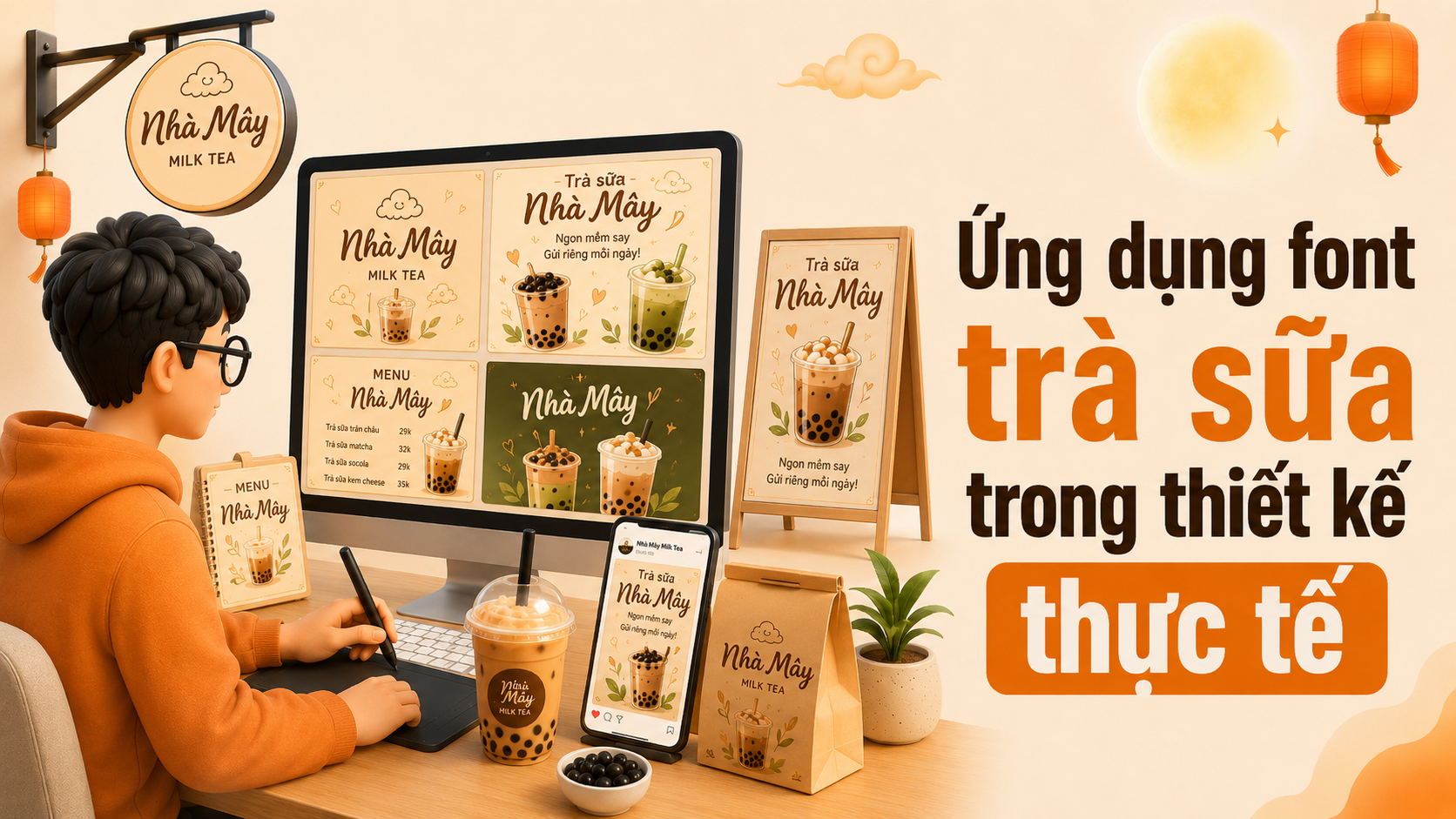
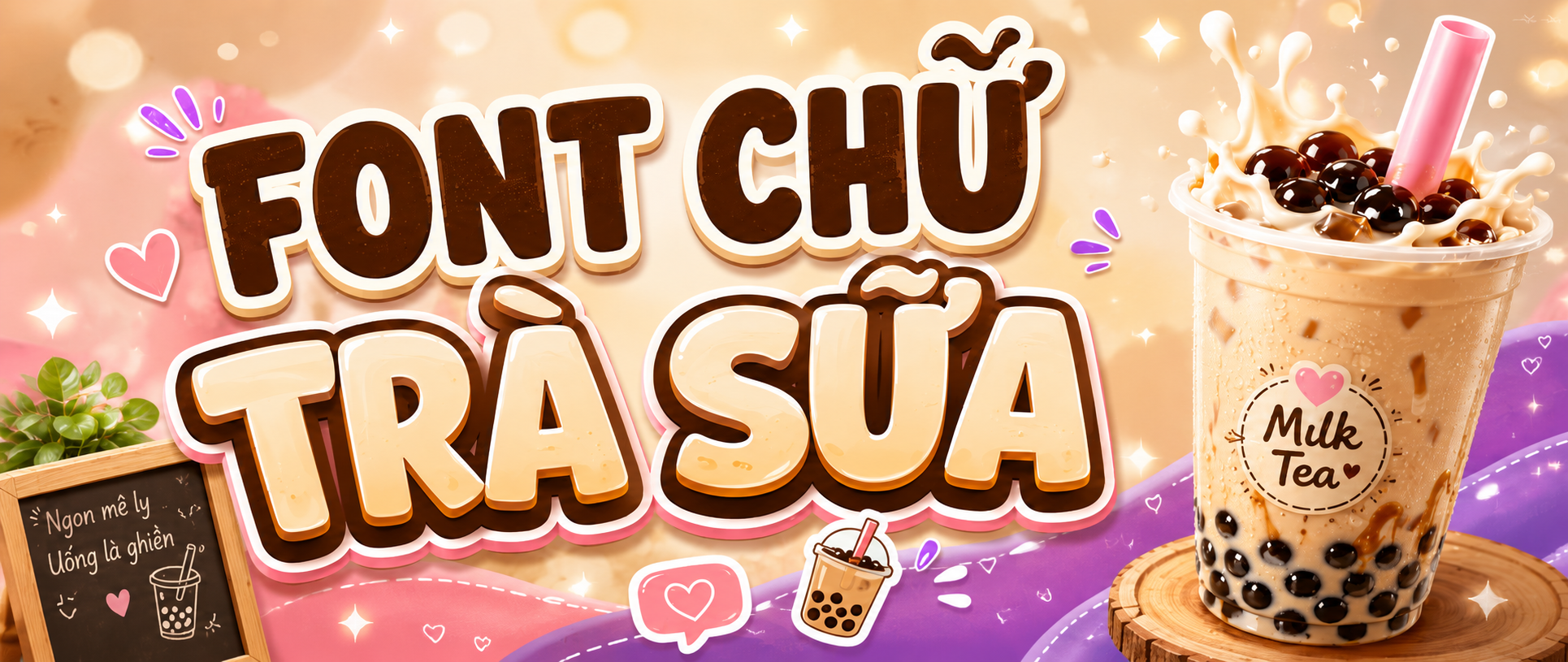
Thiết kế trà sữa cần cảm giác trẻ, ngon, vui và dễ gọi món. Một menu có nhiều topping, size, combo, món mới và giá khuyến mãi sẽ rất dễ rối nếu chọn sai font. Vì vậy, font chữ trà sữa nên vừa đáng yêu, vừa rõ tiếng Việt, vừa đủ nổi bật để dùng cho menu, ly nhãn, poster đồ uống và bảng giá sau quầy.
Bài viết này gợi ý các font TH/Việt hóa phù hợp cho quán trà sữa, đồ uống take away, kem, bánh ngọt và đồ ăn vặt. Mỗi font được đặt thành một dòng riêng kèm link tải trên S99 để bạn dễ chọn, tải và thử vào thiết kế thực tế.
Trà sữa là ngành hàng có rất nhiều thông tin nhỏ: tên món, vị trà, topping, đường đá, size, giá, combo và chương trình ưu đãi. Nếu font quá mảnh hoặc quá cách điệu, khách sẽ khó đọc menu. Nếu font quá cứng, thiết kế lại mất cảm giác ngọt, trẻ và vui.
Font trà sữa thường cần tạo cảm giác thân thiện hơn font nhà hàng. Các nét bo tròn, mũm mĩm, viết tay nhẹ hoặc display cute sẽ giúp menu nhìn gần gũi. Tuy nhiên, không phải phần nào cũng nên dùng font cute. Giá tiền, size và topping vẫn cần font rõ, dễ đọc và căn hàng gọn.
Một thiết kế trà sữa đẹp thường dùng 2-3 kiểu chữ. Font nổi bật dùng cho tên món signature, headline poster hoặc tiêu đề nhóm. Font dễ đọc dùng cho danh sách topping, mô tả, giá và ghi chú. Font phụ có thể dùng cho nhãn nhỏ như “new”, “best seller”, “less sugar” hoặc “combo”.
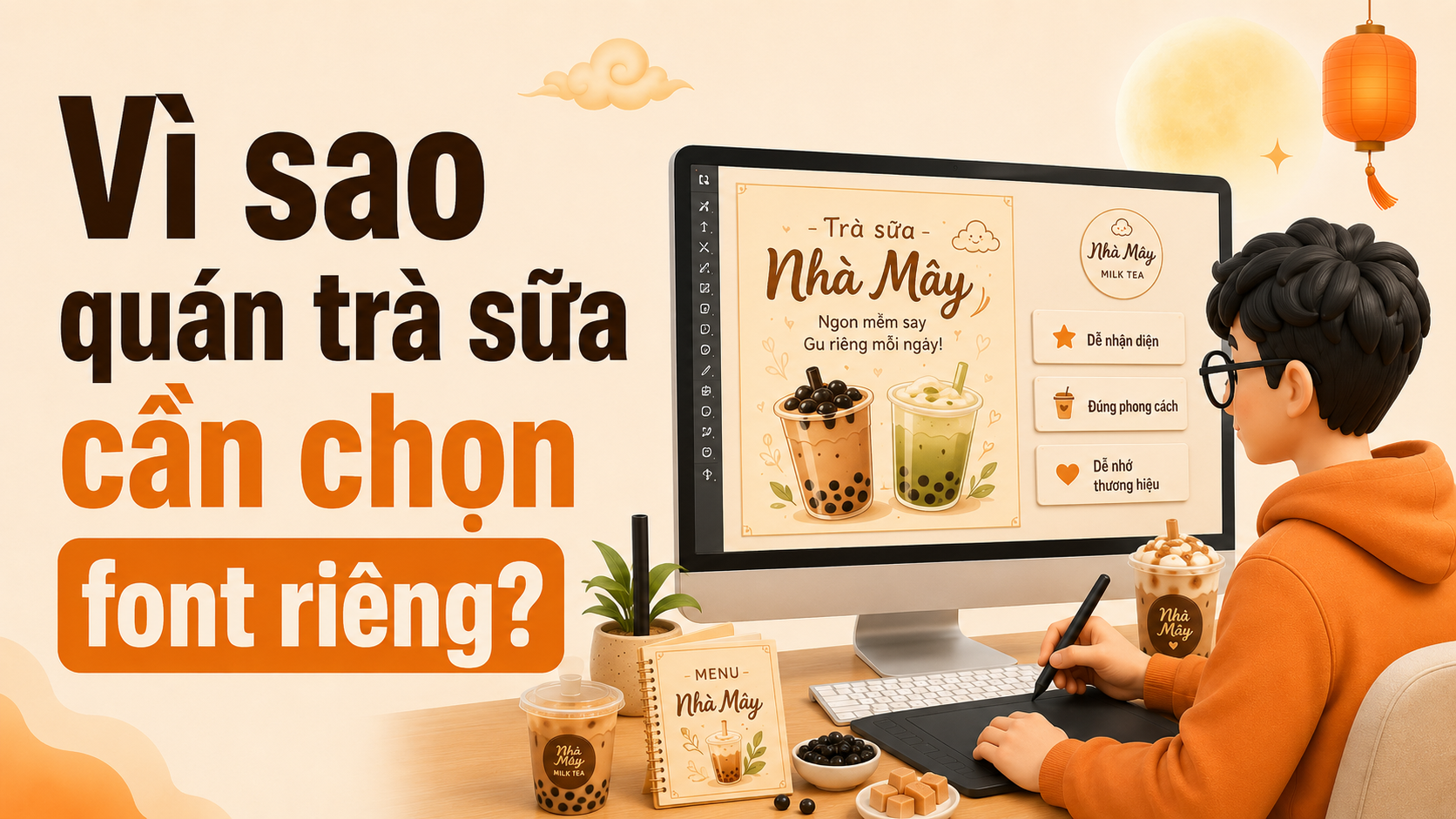
Menu trà sữa có nhiều chữ dễ lỗi dấu như sữa, đường, đá, trân châu, thạch, kem cheese, đậu đỏ, vải, đào, dâu. Font Việt hóa giúp dấu rõ và tránh tình trạng chữ bị lệch, mất dấu hoặc không đồng bộ.
Font mập, bo tròn và hoạt hình rất hợp trà sữa, nhưng nếu dùng cho toàn bộ menu sẽ gây rối. Hãy dùng font cute cho tiêu đề và món nổi bật, còn phần mô tả hoặc giá nên dùng font gọn hơn.
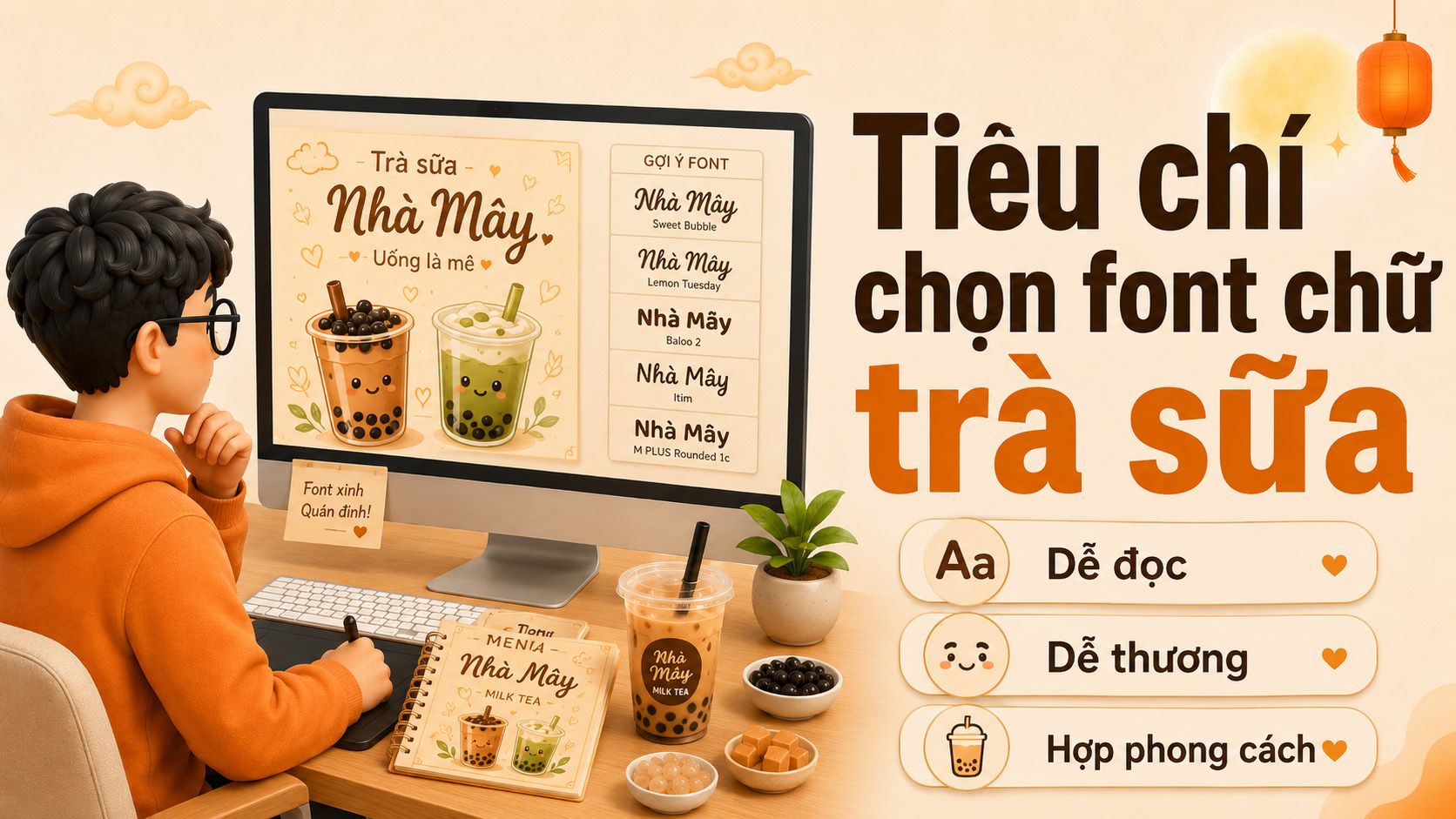
Quán trà sữa pastel hợp font mềm, tròn, nhẹ. Quán trà sữa đường phố hợp font đậm và năng động. Quán trà sữa cao cấp hoặc tea house nên dùng font thanh lịch hơn, tránh quá trẻ con.
Một font tốt nên dùng được cho menu giấy, menu treo tường, ly nhãn, poster Facebook, banner khai trương và story khuyến mãi. Nếu font chỉ đẹp ở cỡ lớn nhưng khó đọc ở cỡ nhỏ, chỉ nên dùng làm headline.
Ảnh ly trà sữa thường có nhiều chi tiết như đá, topping, foam, trái cây. Font cần có nét đủ mạnh để không chìm trên nền ảnh. Nếu nền phức tạp, nên đặt chữ trong khung màu hoặc vùng trắng.
Nhóm này hợp với poster món mới, banner khai trương, menu topping, sticker “best seller” và tên món cần nổi bật. Nét chữ tròn giúp thiết kế nhìn ngọt và vui hơn.
Những font này nên dùng ở kích thước lớn. Ví dụ: “Trà sữa trân châu”, “Matcha kem cheese”, “Combo 2 ly”, “Món mới”. Với bảng giá nhỏ, hãy chuyển sang font sans-serif để giữ độ rõ.
Nếu quán bán thêm bánh, kem, khoai, gà rán, xúc xích hoặc đồ ăn vặt, nhóm font hoạt hình giúp poster nhìn sinh động hơn. Font có cá tính mạnh nên dùng cho điểm nhấn thay vì toàn bộ menu.
Với poster topping, hãy phối font hoạt hình cùng màu sáng như hồng, kem, nâu sữa, xanh mint hoặc vàng bơ. Không nên dùng quá nhiều hiệu ứng viền nếu nền đã có nhiều ly nước và topping.
Font viết tay hợp các quán trà sữa phong cách handmade, nhẹ nhàng, nữ tính hoặc muốn tạo cảm giác thân thiện. Dùng tốt cho slogan, nhãn ly, tên món seasonal và bài đăng social.
Font Cherry Feeling - Tải về
Font TH Friendly Stranger - Tải về
Font TH Mortan - Tải về
Font TH Wellyon - Tải về
Font viết tay không nên dùng cho giá, topping hoặc mô tả dài. Hãy dùng để tạo cảm xúc, ví dụ slogan “ngọt vừa đủ”, “uống là vui”, “fresh everyday” hoặc tên bộ sưu tập mùa hè.
Menu sau quầy cần khách đọc nhanh từ xa. Nhóm font hiện đại, sans-serif và display gọn giúp bảng giá rõ hơn, nhất là khi có nhiều size và topping.
Font TH Namian Sans Serif - Tải về
Font TH Manisans - Tải về
Font TH Giabe - Tải về
Font TH Artega - Tải về
Dùng font cute cho tiêu đề nhóm như “Milk Tea”, “Fruit Tea”, “Topping”, “Best Seller”. Dùng font sans-serif cho tên món, size M/L, giá và ghi chú đường đá. Đây là công thức an toàn nhất cho menu có nhiều món.
Nếu quán dùng màu hồng, kem, xanh mint hoặc tím nhạt, font mũm mĩm sẽ rất hợp. Hãy dùng chữ lớn, khoảng cách rộng và nền sạch để font không bị nặng mắt.
Với poster món mới, dùng font viết tay cho slogan hoặc tên món seasonal sẽ tạo cảm giác tự nhiên. Phần giá và CTA vẫn nên dùng font rõ, ví dụ “Mua 2 tặng 1”, “Chỉ từ 29K”, “Đặt ngay”.
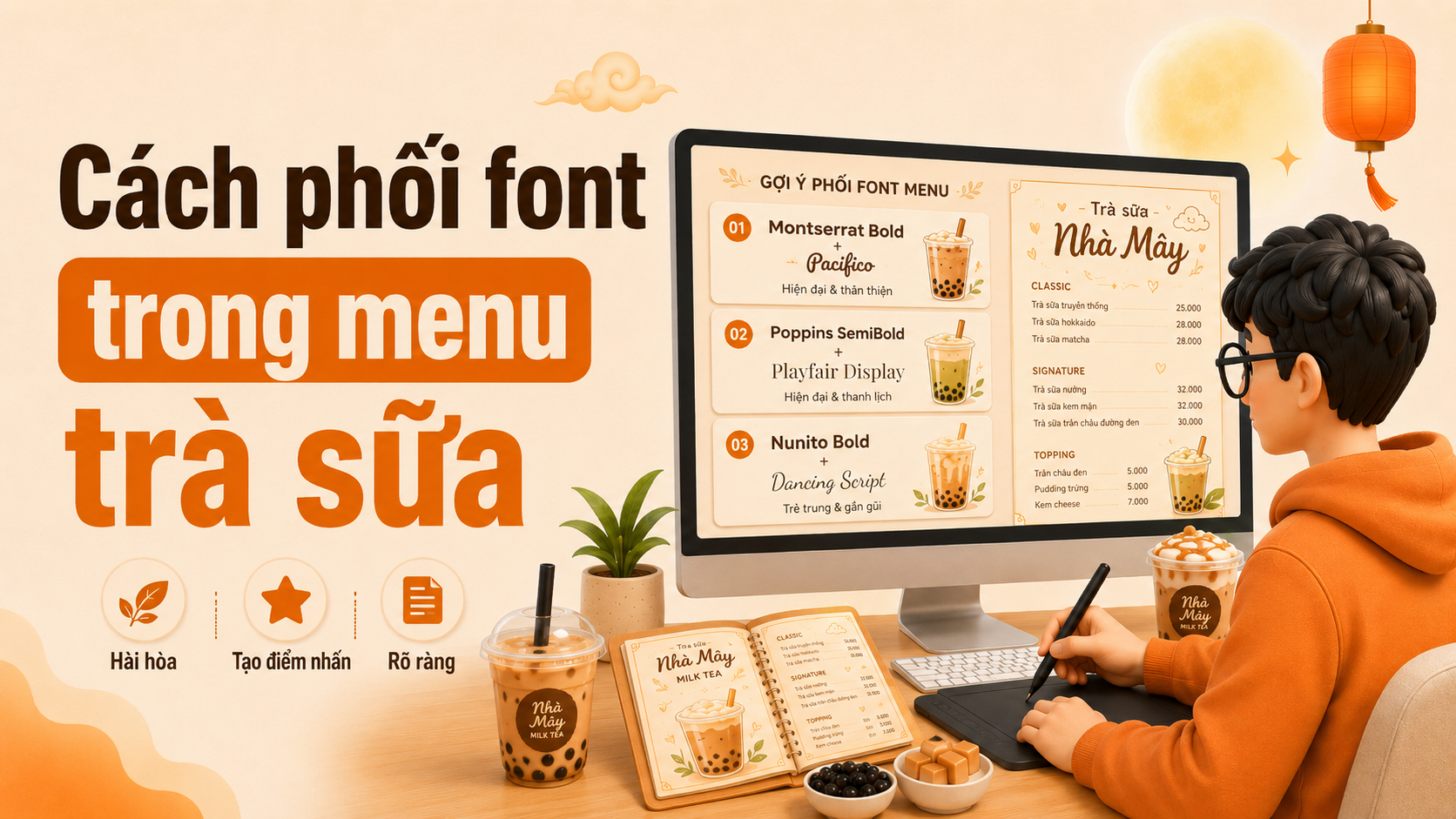
Font hoạt hình hợp sticker nhỏ như “new”, “hot”, “best seller”, “extra topping”. Nên đặt sticker gần ly nước hoặc khung topping, nhưng tránh che sản phẩm chính.
Font chữ trà sữa nên tạo cảm giác trẻ, ngọt và thân thiện, nhưng vẫn phải dễ đọc, hỗ trợ tiếng Việt và dùng được trên nhiều ấn phẩm. Hãy dùng font TH cute cho điểm nhấn, font viết tay cho cảm xúc và font sans-serif hiện đại cho bảng giá, topping, size và CTA.